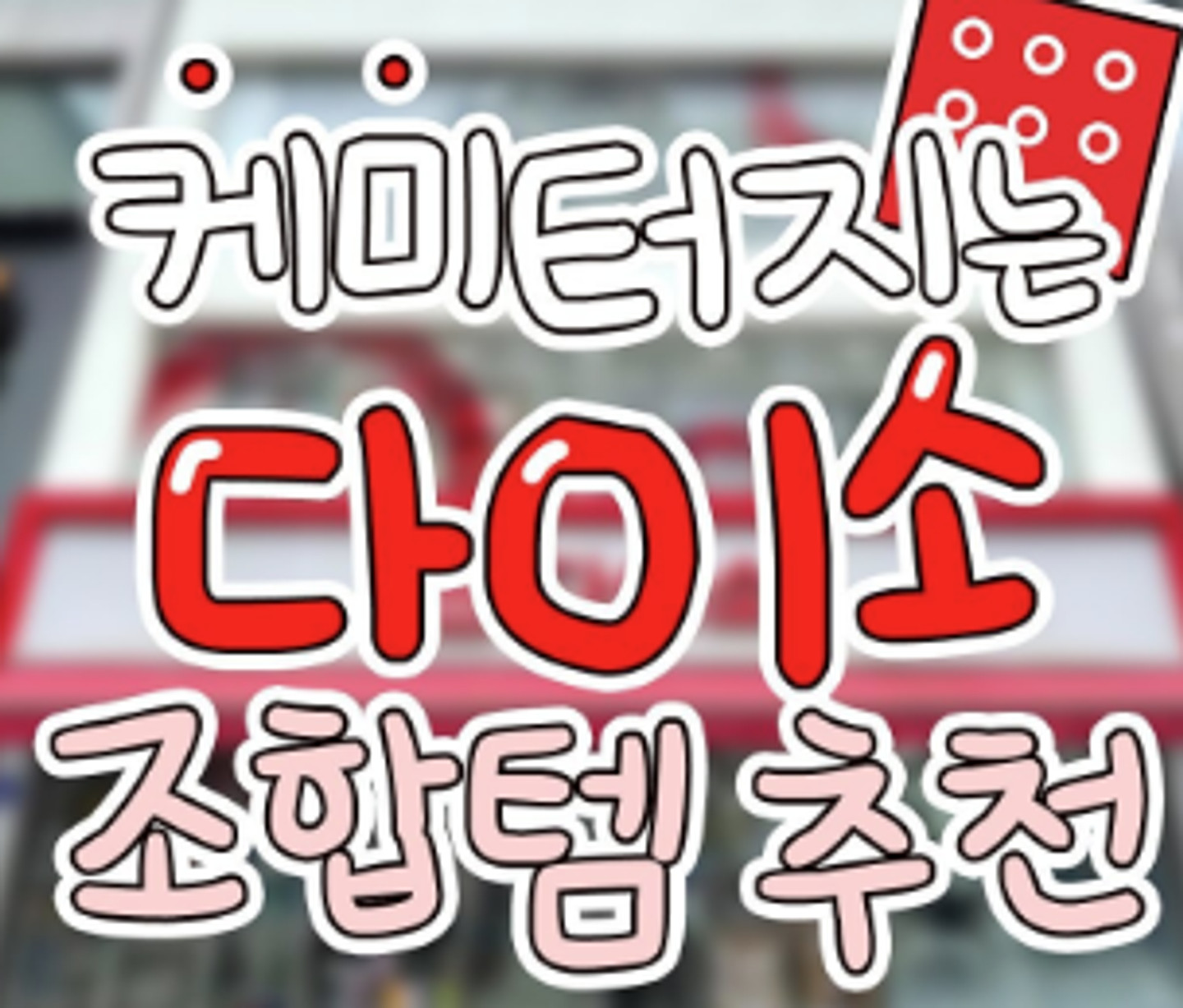
이 폰트 뭔가요 부드러운 느낌의 폰트
매력적으로 보이는데 무슨 폰트일까요? 실제로 사용하고 싶네요.
폰트 이름 알려주새요 ~~
이 폰트 뭔가요 ?
이폰트 이름 알려줘
마카펜으로 쓴거 같은 폰트 입니다
폰트 이름 뭔가요?
이런 느낌의 폰트 있을까요?
저 폰트 궁금해요
글씨체 넘 맘에 쏙 ...알고 계신분 알려주시면 감사합니당
이거 무슨폰트인가요 ㅠㅠ 제발 알려주세요
궁구매요
제발 알려주세요 ㅠ
무슨 폰트 인건가요
이 폰트 많이 보이는데 어떤 폰트인가요?
이 폰트 뭔가용 ㅠㅠ
무슨 글씨인가요
폰트 이름 알고 싶어요.
이 폰트에 대해 아시는 분 계시다면 알려주세요
무슨폰트인지 알 수 있을까요?
이거 무슨 체에요?
궁급합니다!
무슨 폰트일까요? ㅠㅠ 비슷한게 많아서 잘 모르겠네요